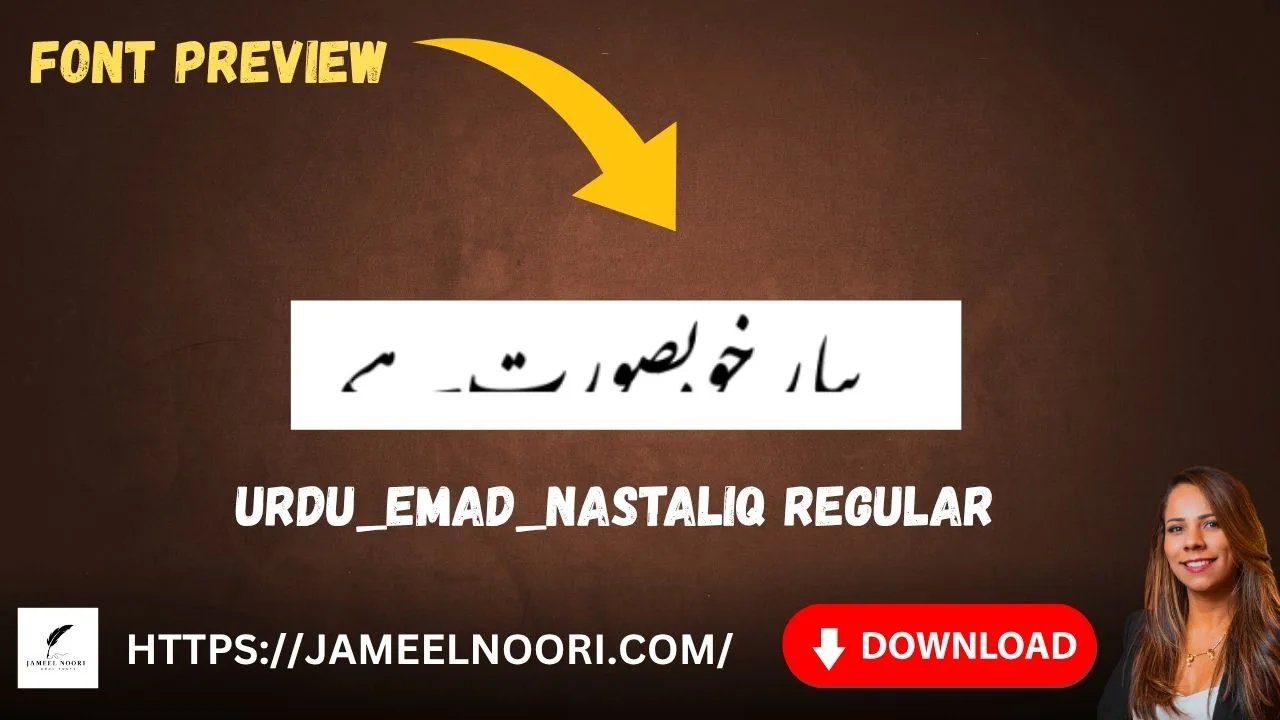
Getting Started with Urdu Emad Nastaliq Regular Font
Urdu Emad Nastaliq Regular Font aik bohat hi khubsurat aur professional Urdu TrueType font hai jo Urdu designers aur writers ke liye perfect choice hai. Ye font readability aur elegance dono ka behtareen combination provide karta hai. Is font ke zariye aap apne Urdu documents, posters, aur graphics me ek stylish touch de sakte hain.
What is Urdu Emad Nastaliq Regular Font?
Urdu Emad Nastaliq Regular aik simple aur smooth Urdu typeface font hai jo professional aur creative designs ke liye use hota hai. Ye free urdu font apni clean curves aur accurate Nastaliq style ki wajah se designers me bohat popular hai.
Features of Urdu Emad Nastaliq Regular (TTF) Font
Ye features clearly show karte hain ke Urdu Emad Nastaliq Regular Urdu Font ek trusted aur reliable font hai jise professionals regularly use karte hain.
Why Choose Urdu Emad Nastaliq Regular Font?
- Best Urdu font for daily writing and professional design
- Aapko stylish font look milta hai jo classic Nastaliq feel deta hai
- Har text aur heading me smooth flow aur beautiful curves nazar aate hain
Urdu Emad Nastaliq Regular Urdu Font designers ke liye ek ultimate choice hai jo apne Urdu projects ko premium look dena chahte hain.
Usage Ideas for Urdu Emad Nastaliq Regular Font
- Urdu books aur eBooks design karne ke liye